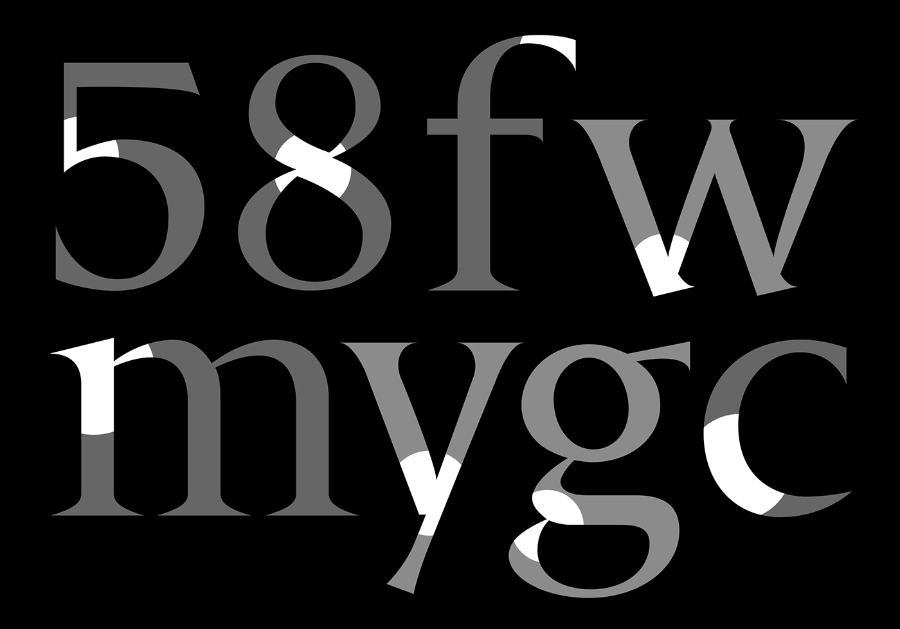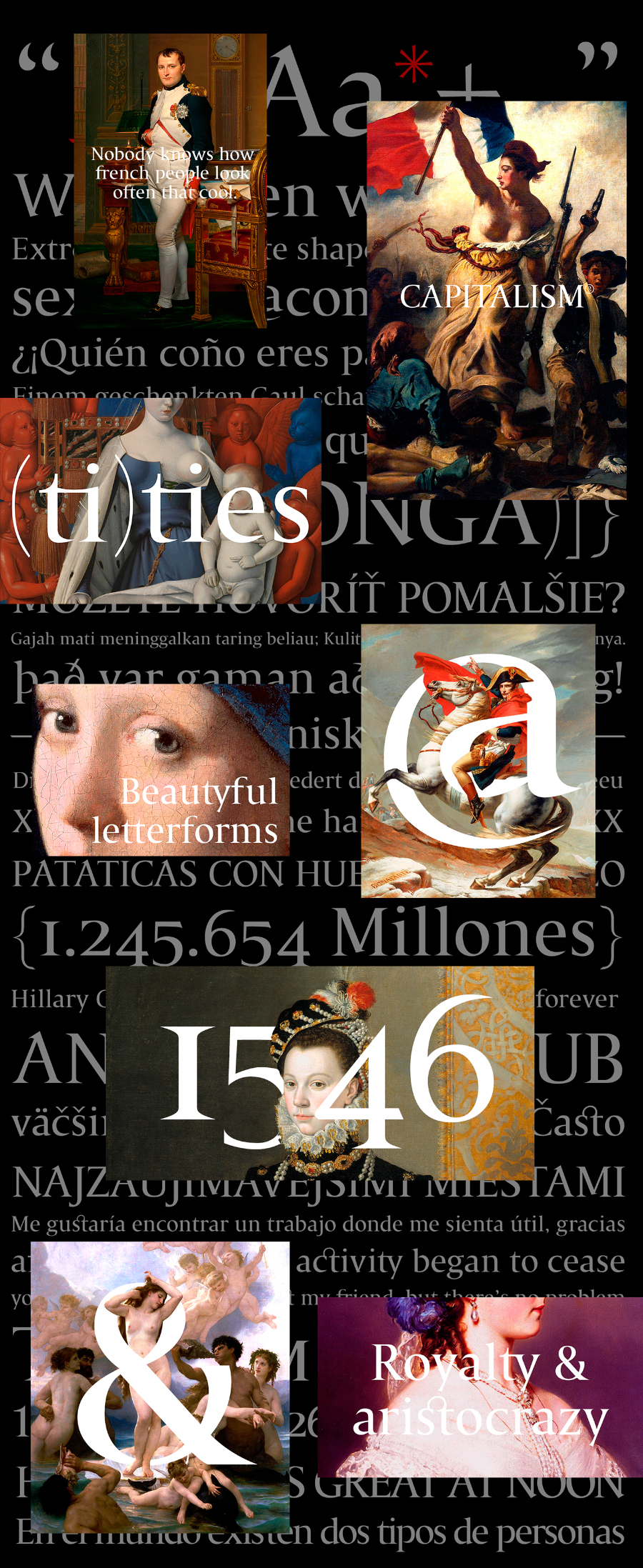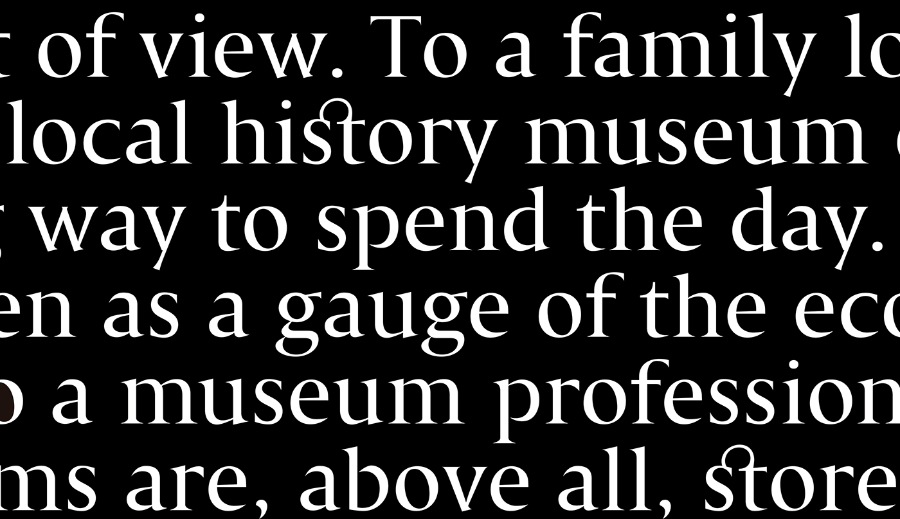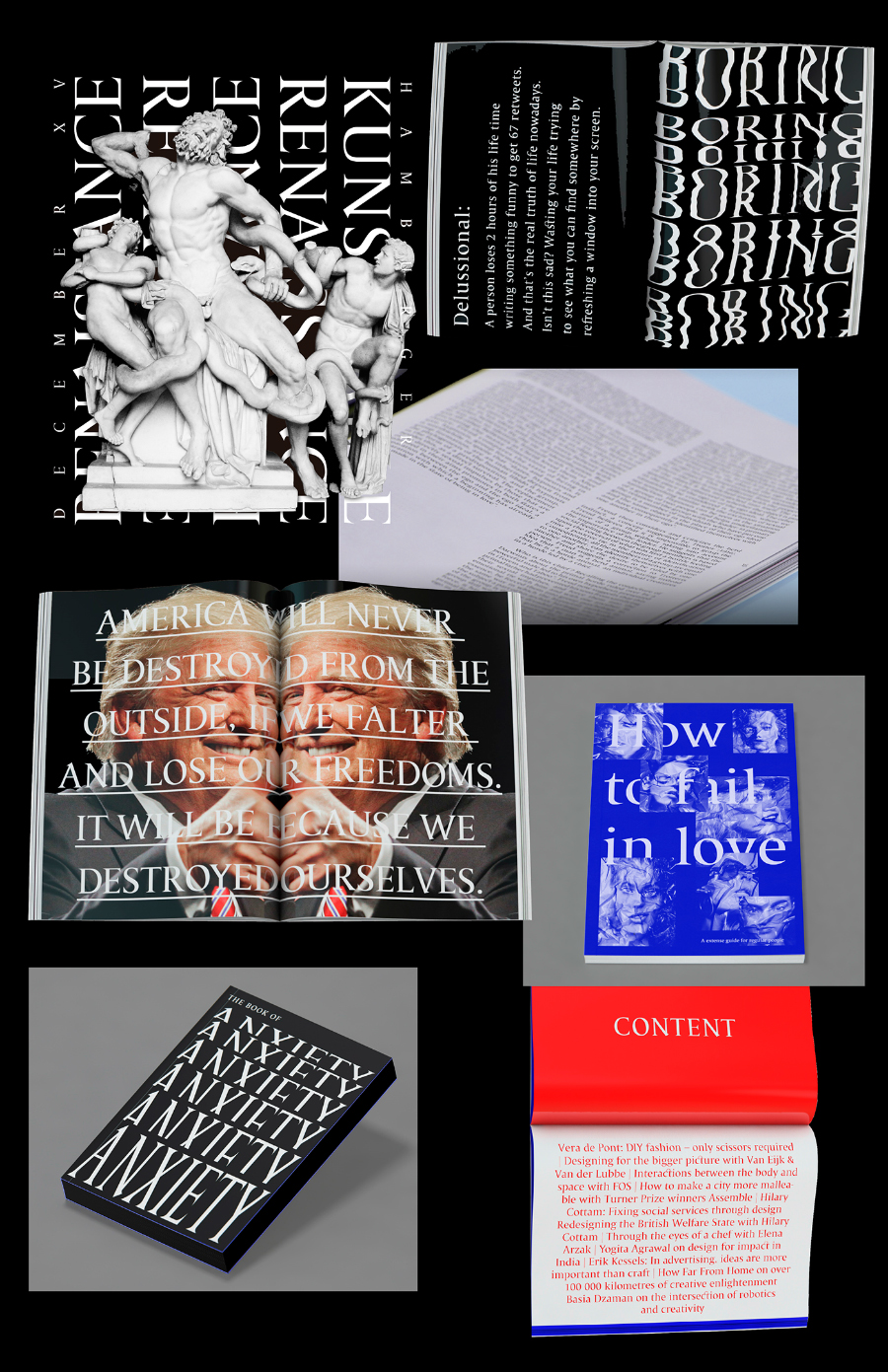
Fea人文主义者自由字体
Fea Humanist Serif Free字体是基于Swift的字体。它来自十五世纪末罗马字母的灵感。它非常适合任何类型的杂志,书籍,报纸,小册子,报告等编辑用途。尽管从书法形状的建设经典的外观和高对比度,其前卫细节和对比不规则的关节将使其完美的任何目的。它可以很好地适用于小尺寸和大尺寸。它带有800多个字形和许多opentype功能,以满足您所有的可能的需求。